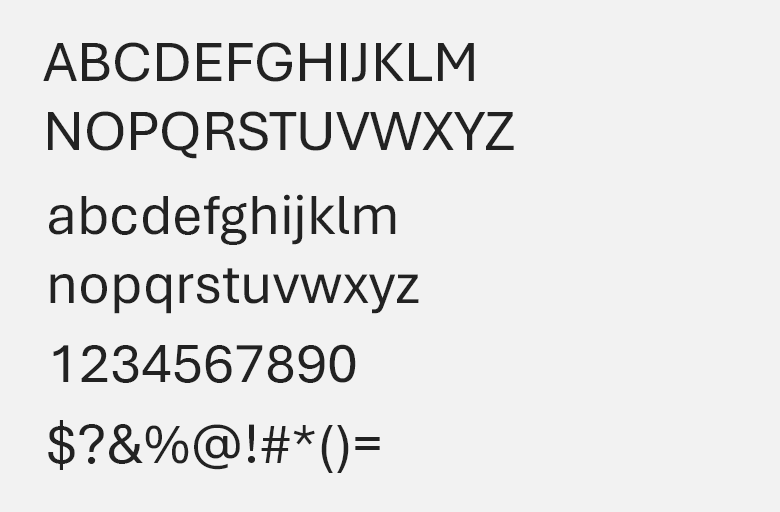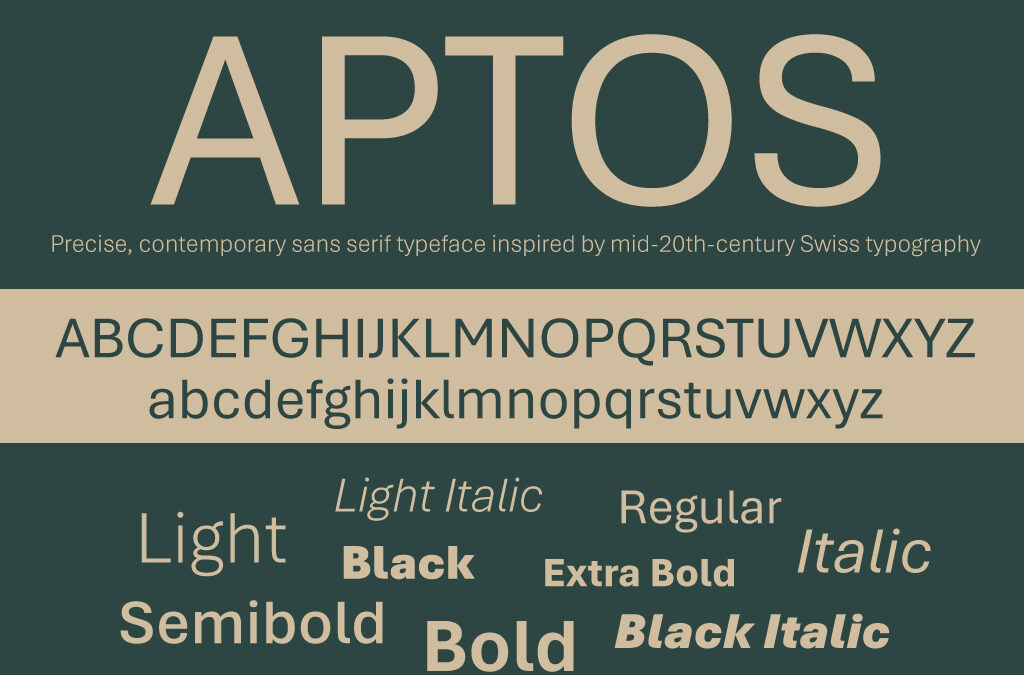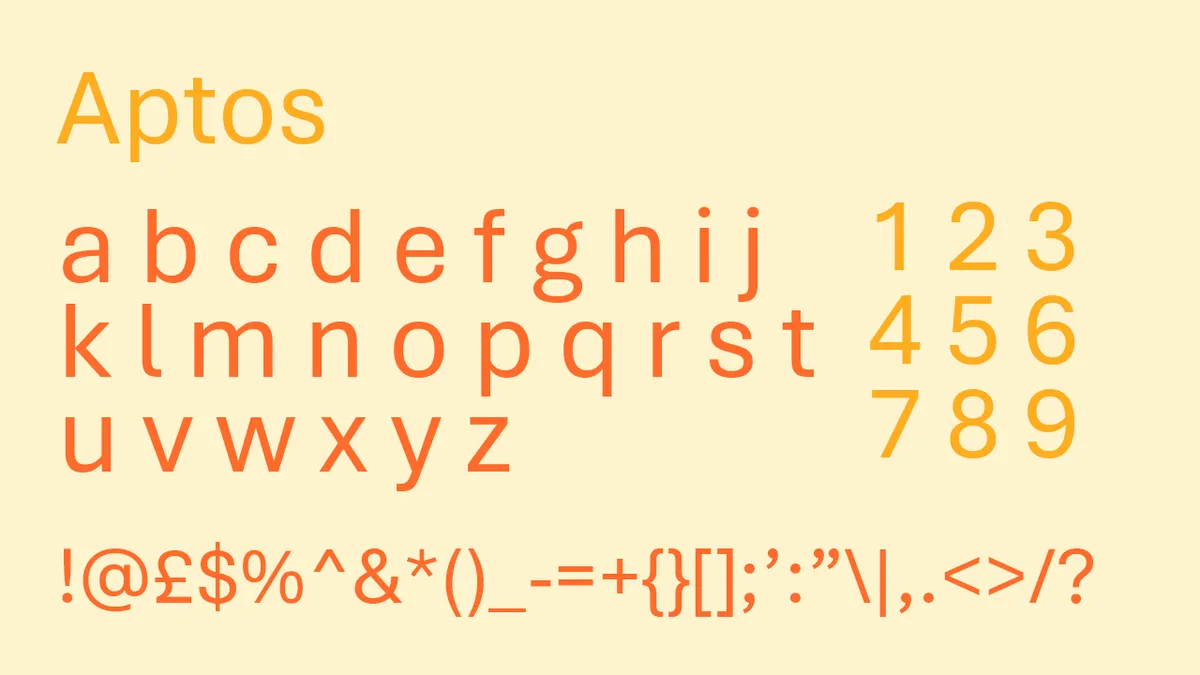
Download font Aptos là nhu cầu mới nhất của giới thiết kế khi Microsoft chính thức lựa chọn bộ phông chữ này thay thế cho Calibri huyền thoại làm phông mặc định cho bộ ứng dụng Office. Được thiết kế bởi Steve Matteson, Aptos (tên gọi cũ là Bierstadt) mang phong cách Sans-serif hiện đại, tối giản nhưng vô cùng ấm áp và dễ đọc. Doozypack.vn chia sẻ link tải font Aptos trọn bộ với đầy đủ các biến thể, giúp bạn sở hữu phông chữ thời thượng nhất để thiết kế bao bì, hồ sơ năng lực và giao diện số chuyên nghiệp.
Đặc điểm thiết kế đột phá của bộ font Aptos
Aptos không chỉ đơn thuần là một sự thay đổi giao diện; nó là kết quả của việc nghiên cứu trải nghiệm đọc trong kỷ nguyên màn hình độ phân giải cao và in ấn kỹ thuật số sắc nét.
Mẫu chữ Aptos hiện đại
Phong cách hiện đại dựa trên cảm hứng Thụy Sĩ
Đặc trưng lớn nhất của font Aptos là cấu trúc chữ dứt khoát lấy cảm hứng từ Typography Thụy Sĩ thế kỷ 20, nhưng được làm mềm mại hơn bằng các đường cong nhân văn (humanist). Thiết kế này giúp các ký tự không bị khô cứng như Helvetica, mang lại cảm giác minh bạch và thân thiện. Khoảng hở trong chữ (counter) được tính toán tỉ mỉ giúp phông chữ duy trì được độ rõ nét tuyệt vời ngay cả khi trình bày ở mật độ văn bản dày đặc.
Khả năng hiển thị đa năng trên mọi nền tảng
Dù bạn sử dụng aptos download font để soạn thảo văn bản hành chính hay làm tiêu đề cho các mẫu bao bì cao cấp, phông chữ này vẫn thể hiện được sự ổn định đáng kinh ngạc. Các đầu nét chữ được cắt gọn gàng, độ dày nét đồng đều giúp mắt người nhận diện mặt chữ cực nhanh, giảm thiểu tình trạng mỏi mắt khi theo dõi các khối văn bản dài trên catalogue hay mặt sau hộp giấy.
Hệ sinh thái Aptos Font Family đa dạng biến thể
Khi thực hiện tải font Aptos, bạn sẽ sở hữu một hệ gia đình phông chữ phong phú, đáp ứng mọi nhu cầu phân cấp thông tin trên bản thiết kế:
• Aptos Display: Có cấu trúc chữ thanh thoát và sắc sảo hơn, lý tưởng để làm Logo hoặc tiêu đề chính thu hút thị giác.
• Aptos Serif: Phiên bản có chân dành cho những thiết kế cần sự trang trọng, cổ điển và uy tín.
• Aptos Mono: Phông chữ đơn cách, phù hợp cho các thiết kế mang tính kỹ thuật, mã số hoặc thông số sản phẩm.
• Aptos Narrow: Biến thể hẹp giúp tối ưu không gian hiển thị trên các mặt bên của hộp giấy nhỏ.
Kiểu chữ Aptos chuyên nghiệp
Biến thể Font Đặc điểm thị giác Ứng dụng đề xuất tại Doozypack.vn
Aptos Regular/Light Cân đối, dễ đọc Dùng cho nội dung hướng dẫn sử dụng, bảng thành phần (Body text).
Aptos Bold/Black Vững chãi, nổi bật Dùng làm tiêu đề phụ, tên sản phẩm hoặc slogan trên túi giấy.
Aptos Display Sắc sảo, thời thượng Thiết kế Logo, tiêu đề chính trên hộp quà tặng cao cấp.
Tư vấn từ chuyên gia: Nếu bạn đang thiết kế bao bì cho các dòng sản phẩm công nghệ hoặc startup, hãy sử dụng font Aptos Bold cho tên thương hiệu. Sự hiện đại và minh bạch của khối chữ Aptos sẽ tạo niềm tin rất lớn cho khách hàng ngay từ cái nhìn đầu tiên.
Tại sao designer nên chọn font Aptos cho thiết kế bao bì?
Trong ngành thiết kế và sản xuất bao bì tại Doozypack.vn, Aptos luôn nằm trong danh mục các font chữ “vàng” nhờ tính ứng dụng thực tế cao:
• Cập nhật xu hướng: Sử dụng Aptos giúp bản thiết kế của bạn bắt kịp ngôn ngữ đồ họa mới nhất của Microsoft, mang lại vẻ ngoài tân thời cho sản phẩm.
• Độ hiển thị sắc nét ở kích thước nhỏ: Cấu trúc Sans-serif hiện đại của Aptos giúp các thông tin chi tiết trên tem nhãn vẫn cực kỳ rõ nét, không bị bết mực khi in hàng loạt.
• Tính chuyên nghiệp: Vẻ ngoài trung tính nhưng tinh tế của Aptos rất phù hợp với các dòng bao bì dược phẩm, thực phẩm chức năng và linh kiện điện tử.
Thiết kế typography dễ đọc